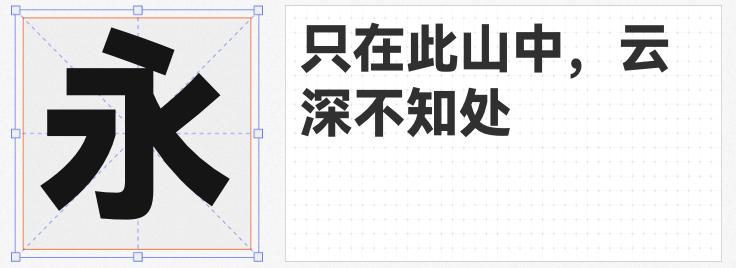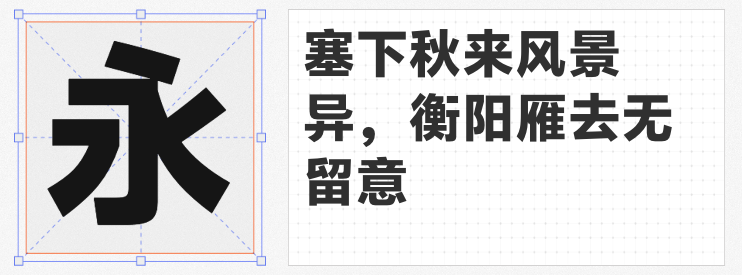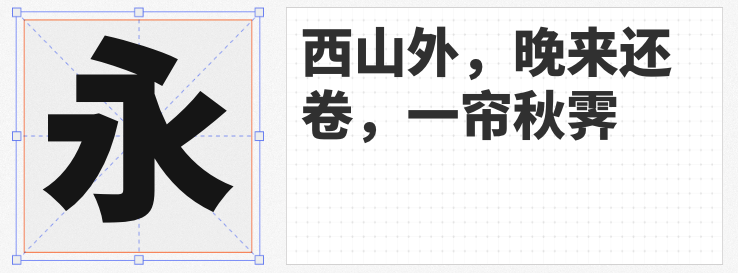
在品牌视觉升级与数字内容创作中,黑体因其简洁现代、易读性强的特性,成为设计师的首选字体类型。本文精选四款免费商用黑体,涵盖科技感、人文感与跨平台适配性,助力设计师高效打造高品质视觉作品。
作为华为推出的系统级字体,HarmonyOS Sans SC Black以“易读性、独特性、通用性”为核心,通过优化可变字体笔画连接处的细节,显著提升小字号下的清晰度。其结构融合现代几何感与书写韵律,较Roboto更显宽大舒展,尤其适合深色模式下的动态字重调整,确保不同屏幕显示的一致性。无论是UI界面还是海报标题,均能传递专业与温度并存的视觉感受。
由Adobe与Google联合开发的思源黑体,思源黑体 SC Heavy版本以方正字形与适中中宫比例,构建出平衡感极佳的排版效果。利落的直角笔型与均匀的粗细对比,搭配断开连接的笔画设计,赋予字体简约干练的气质。在数据图表、新闻标题等需要强调权威性的场景中,其清晰有力的视觉表现力尤为突出。
基于多款开源字体融合优化的句读黑体,支持中文、日文、拉丁字母等数十种语言,是跨国品牌与多语言项目的理想选择。句读黑体 Hans Heavy版本保留了黑体的现代感,同时通过微调字面率与字间距,提升复杂排版下的可读性,尤其适合需要兼顾文化包容性的设计场景。
vivo Sans以“去装饰化”为设计哲学,通过精细的结构优化与笔画减法,打造出极致简洁的视觉效果。Heavy版本在保证粗壮字重的同时,避免笔画臃肿,确保小字号下的清晰度,非常适合长文本阅读场景,如电子书、品牌手册等,帮助用户聚焦内容本身。
这四款免费商用黑体各具特色,无论是追求科技感、经典稳重还是全球化适配,均能满足专业设计需求。合理运用它们,可显著提升作品的视觉层次与信息传达效率。